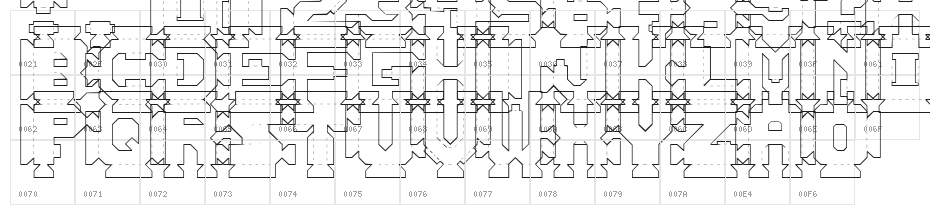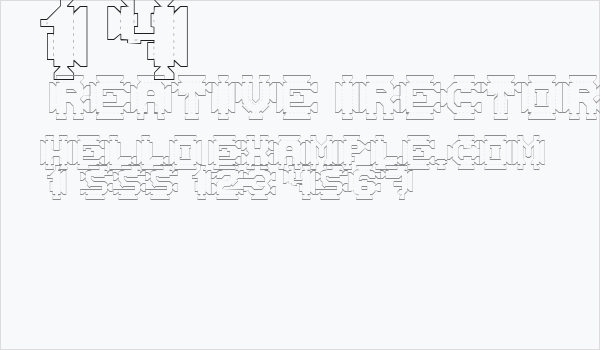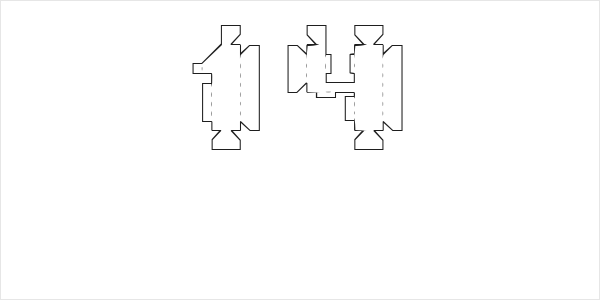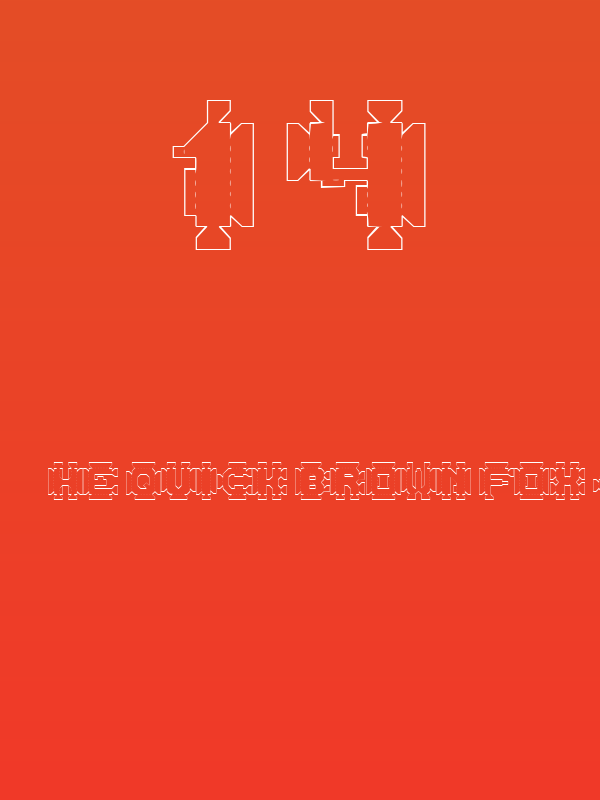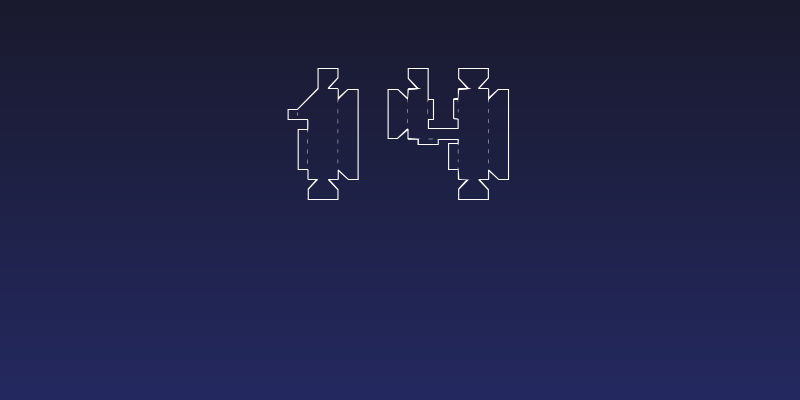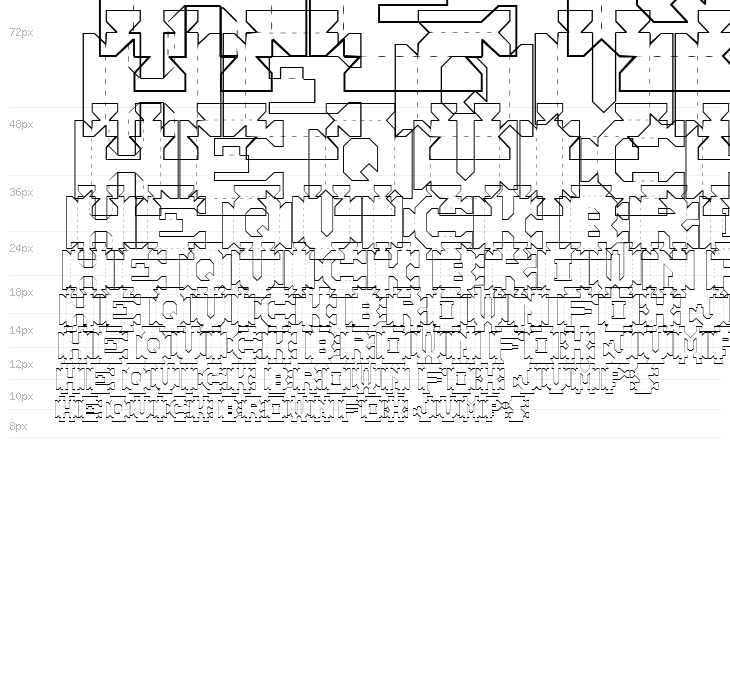
1:4 Font
| Stile generale | Futuristic, Mechanical |
| Progetti proposti | Ideal for sci-fi themed posters, video game titles, futuristic branding, and digital art projects. |